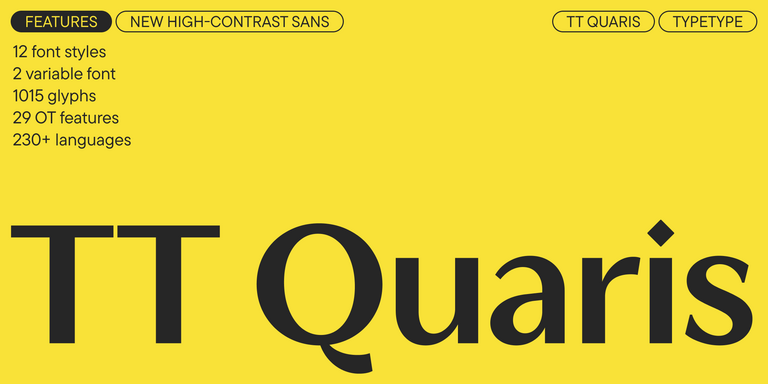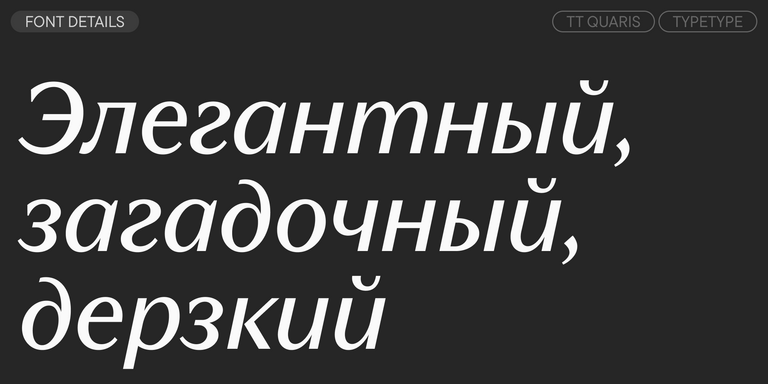
Подборка Романшских+ шрифтов
Выберите подходящий шрифт с поддержкой Романшского+ языка. Огромная коллекция шрифтовых семейств для любых целей и задач: набор больших текстовых массивов, оформление заголовков для веб-сайтов и печатных изданий, печать на текстиле и других материалах, оформление вывесок и афиш.
Каждый из представленных шрифтов содержит Романшский+ алфавит. Широкий выбор символов, знаков валют и пунктуации, шрифтовых начертаний и OpenType фич позволят применять один шрифт для разных проектов. Знаки расширенной латиницы, содержащие диакритические знаки, расширят возможности использования шрифта для разных стран.
Каждый шрифт безупречен с технической точки зрения. Многие шрифты из коллекции содержат вариативное начертание, с помощью которого можно создавать уникальное начертание для проекта.
TT Polihaus — экспериментальный гротеск, который на первый взгляд кажется обычным, а затем разбирается на части, превращаясь в трафаретный узор.
TT Odellia — старостильная антиква с современным рисунком, вдохновлённая венецианскими шрифтами и классической музыкой.
TT Nooks Serif — акцидентная новостильная антиква с лёгким налётом эгоцентричности. У неё острый и твёрдый, при этом элегантный и статный характер.
TT Nooks Script — шрифт с уникальным рисунком, который не имеет прямых аналогов.
TT Supermolot Neue — технологичный модульный гротеск с футуристическим настроением и мощным функционалом. Яркость его характера сочетается с универсальностью применения.
TT Runs — это выразительный шрифт, который идеально впишется в проекты со спортивной тематикой. При этом гарнитура отлично подойдет и для других современных проектов: после обновления сфера ее применения значительно расширилась.
TT Bells сочетает в себе элегантную мягкость антиквы с непростым и дерзким характером, который выражается в прямых срезах и клинообразных засечках. В основе шрифта лежит ширококонечное перо, характерное для старостильных шрифтов, создающее эти атмосферные срезы и засечки.
TT Severs — это геометрический гротеск с ярко выраженными элементами внутренних скруглений. Отличительной особенностью TT Severs является необычная форма внутренних овалов, которая отсылает нас к стилю традиционной арабской письменности.
TT Norms® Pro — один из самых востребованных шрифтов студии, выбор известных мировых брендов. Более трёх переизданий за семь лет, первые строчки на MyFonts, десятки кастомизаций. Это «рабочая лошадка», которая станет незаменимой базой любой шрифтовой коллекции.
TT Commons™ Pro — один из самых востребованных шрифтов студии. Сфера его применения практически безгранична! Беспроигрышный вариант для тех, кто ищет стильный и функциональный базовый шрифт для любых проектов.
TT Hoves Pro — скандинавский гротеск с нейтральным, но в то же время узнаваемым характером. Это удобный и функциональный, при этом стильный и эстетичный инструмент для дизайнеров. Такой шрифт позволит вам решать множество разноплановых задач!
TT Supermolot Neue — непобедимое оружие в борьбе за стиль! Это технологичный модульный гротеск с футуристическим настроением и мощным функционалом. Шрифт идеально подойдёт для оформления компьютерных игр и множества других проектов.
TT Firs Neue — сбалансированный гротеск со скандинавскими мотивами. Это выразительный и привлекательный, при этом лаконичный и универсальный в использовании шрифт. Переиздан дважды, чтобы быть безупречным.
TT Rounds Neue — мягкий и дружелюбный шрифт, который умеет быть разным. В тонких начертаниях он выглядит минималистично и нейтрально. В жирных же — «надувается» и округляется, приобретая инфантильные черты.
TT Fors — тот самый шрифт «для всего». Это стильный, лаконичный и функциональный геометрический гротеск с выверенными формами. Его можно использовать и в интерфейсах, и для создания акцентов.
TT Marks — рукописный шрифт с динамичным ритмом, тёплым характером и слегка ностальгическим настроением. Он вдохновлён классическими американскими расписанными вывесками (sign painting), которые когда-то художники создавали вручную с помощью кистей и красок. Сегодня надписи в таком стиле снова набирают популярность.
TT Fellows — гуманистический гротеск с механистическими мотивами. Открытые формы, дружелюбно-нейтральный характер тонких весов и ещё более мягкий характер в жирных начертаниях.